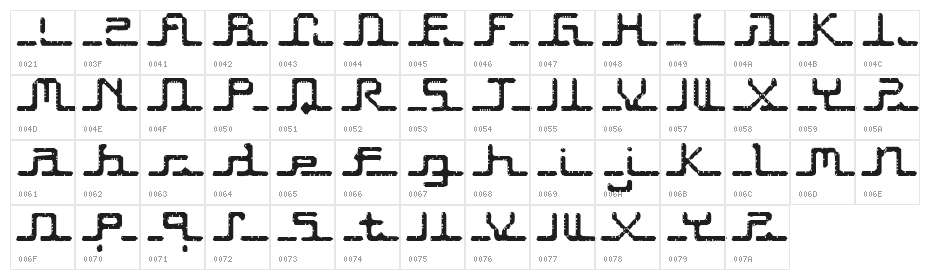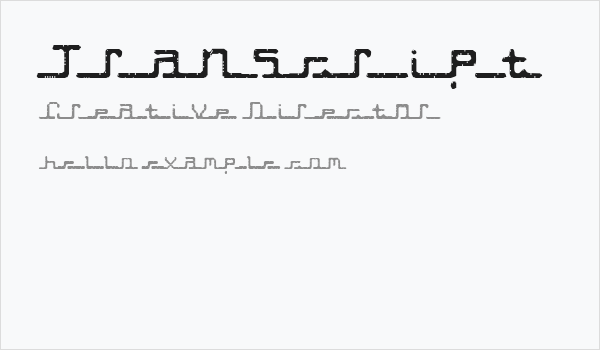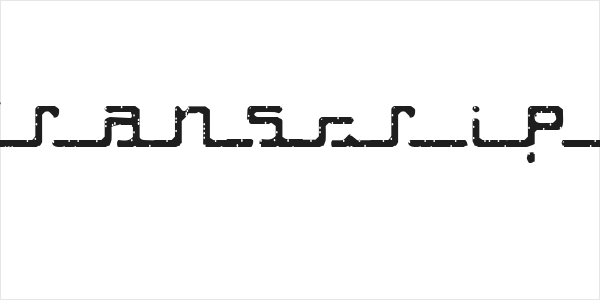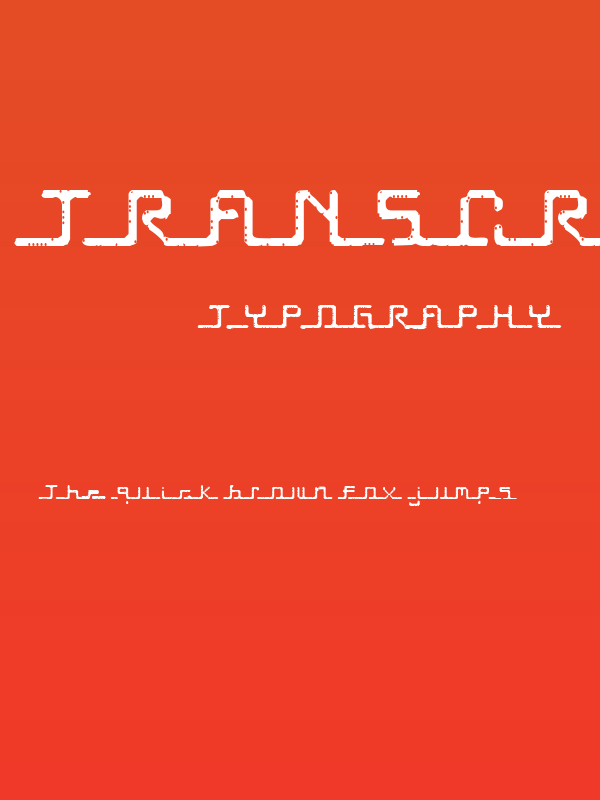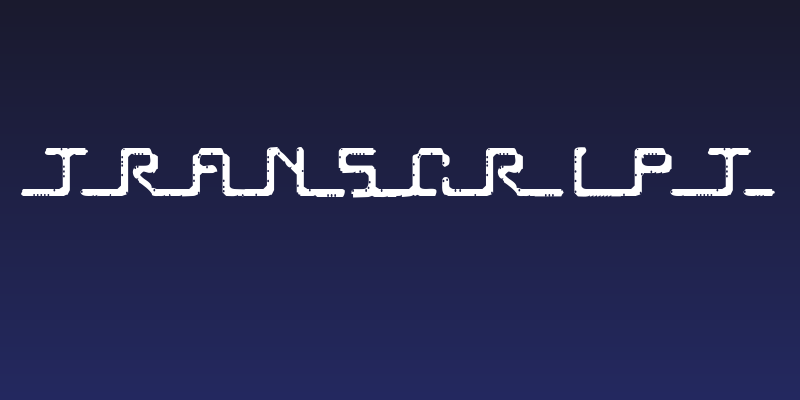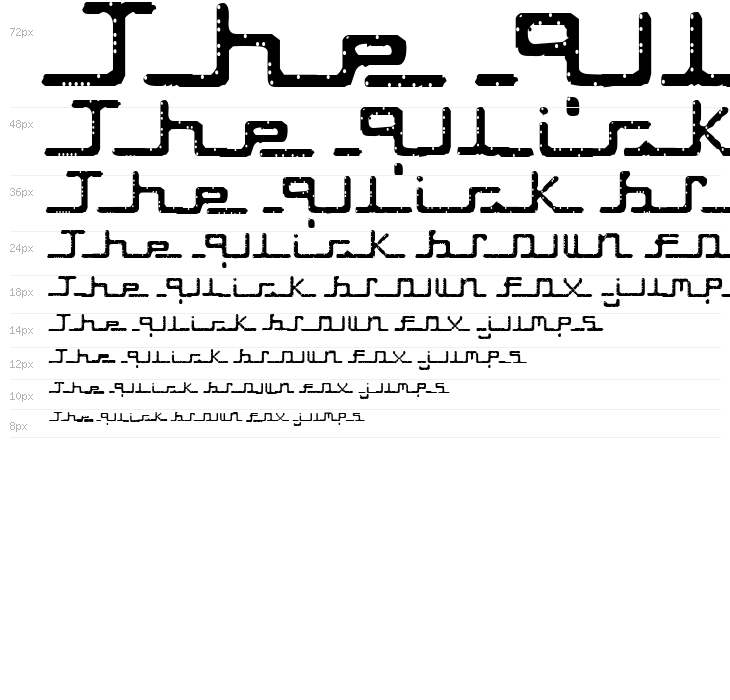
Transcript Font
| Categorie | Quirky |
| Stile generale | Futuristic |
| Caso d'uso | Logos, Tech interfaces, Digital art |
| Progetti proposti | Ideal for tech branding, digital art projects, sci-fi themed designs, and coding interfaces. |